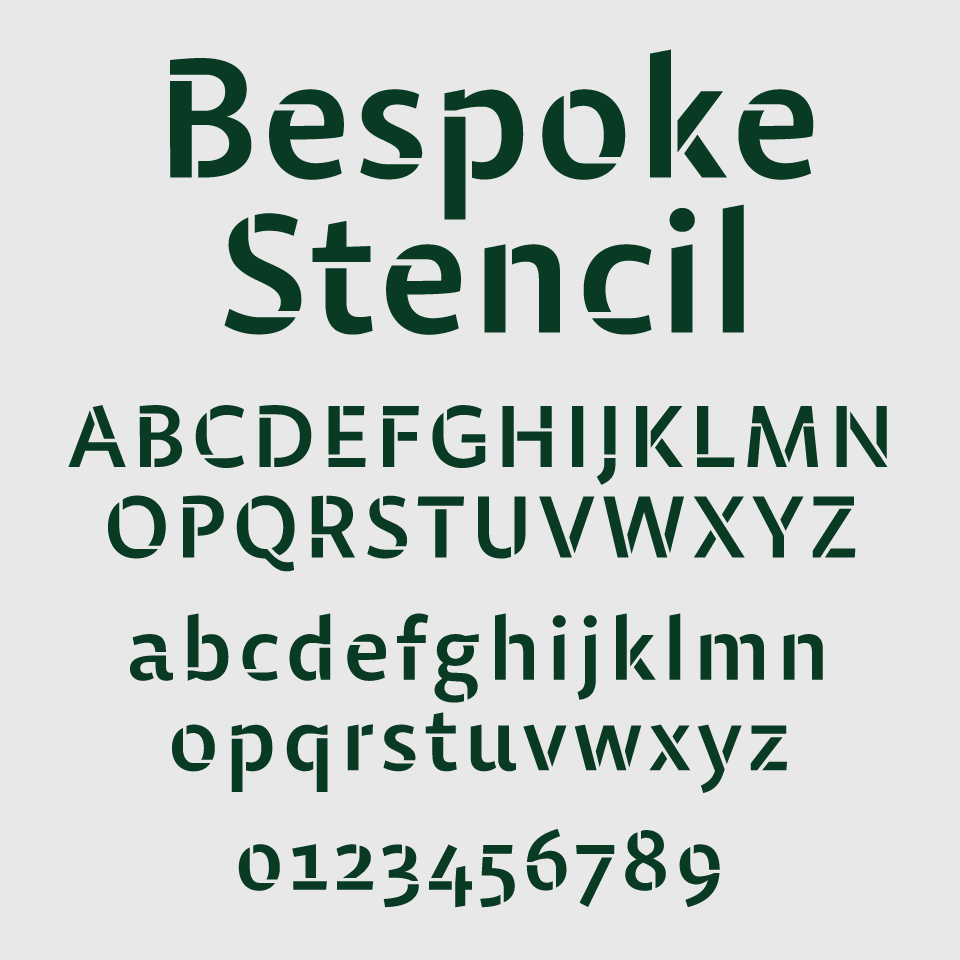
Bespoke Stencilは、サンセリフ体のなめらかさと、ステンシルらしい無骨さを絶妙に掛け合わせたフォントです。切り離された部分のバランスが秀逸で、読みやすさを損なわずにグラフィカルな印象を与えています。
ザ・ステンシル、といったより少しスリットを入れたオシャレミリタリー感感じるカッコよさのあるデザインです。